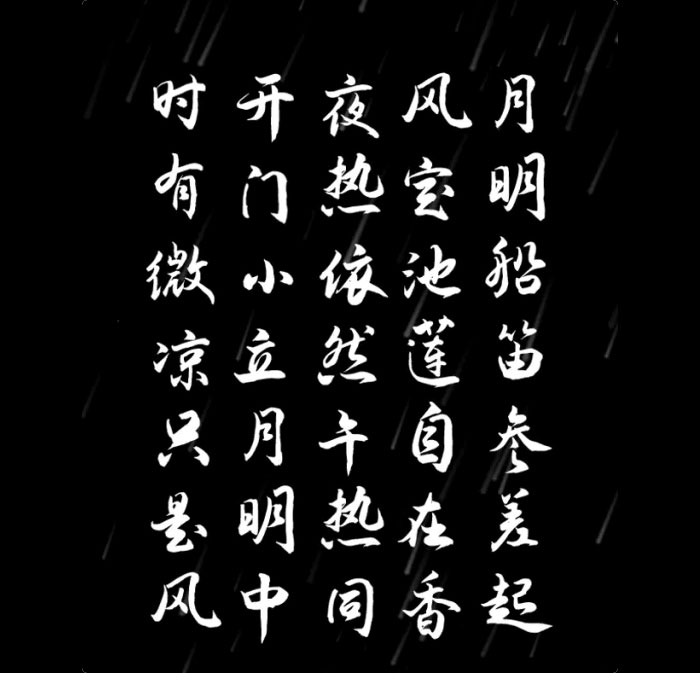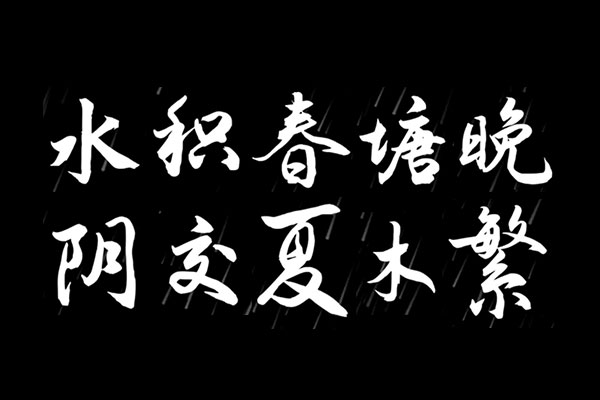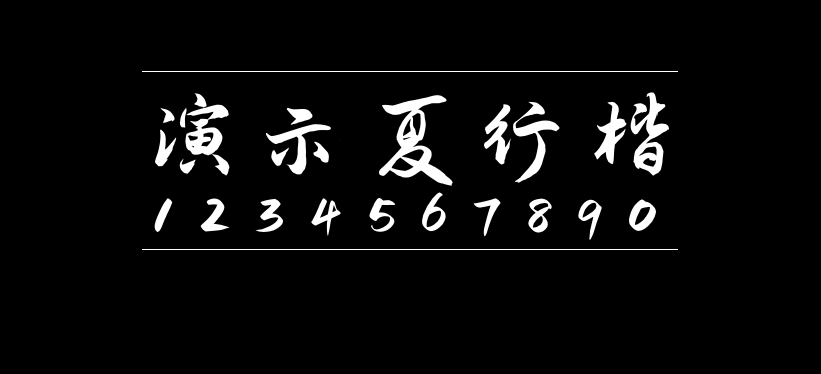
演示夏行楷
演示夏行楷是Keynote研究所的人生哥制作发布的一款毛笔字体。字稿作者是刘锡栋:中国漓江书画艺术家协会理事丨北京中国书画研究院研究员丨中国民族硬笔书法家协会会员丨中国楹联学会会员丨黑龙江楹联家协会会员丨高级政工师,已退休
该字体简体中文行楷,包含标准的6763个字符。
以下为作者原文的引用:
你好,这里是 Keynote研究所,我是人生哥。
设计,重要的是,如何解决用户所面临的当前问题
两年前,为了解决在 Keynote 中文字不能倾斜的问题,我做了一次大胆的尝试:自己动手改造出一款 Keynote 可用的倾斜字,让幻灯片设计师可以在Keynote中一键倾斜文字。于是基于对谷歌开源字体「思源黑体」的倾斜处理,便有了 — 演示斜黑体。但很多人说,这款字应该叫做 演示斜杠体,因为是它,让关于我的故事不再是只有PPT,又加上了一道斜杠——字体。
优秀幻灯片,集巧妙的逻辑编排与可视化图形语言于一身,使原本枯燥的内容,变得更加易懂且利于表述,甚至可以引起大范围传播
发展到今天,PPT 已经不局限于“大字报工具”,它更像是一个多媒体容器,集合了图形语言、图标元素、风格字体、图片视频、3D模型·········从“实用为先”到兼顾“策略与颜值”的双重美学。甚至,它已为很多人创造了就业机会,当然也包括我。
商业幻灯片委托,不仅要帮客户完成项目,更要帮他们规避风险
事实上,大多数风险行为与字体和图片侵权有关,这源自仍有很多企业对于版权意识的淡薄,以及少有能力去支付高昂的授权费。虽然字体和图片被称作是设计师的“油盐酱醋”,但实际情况却是:好字体不敢用,好图片没钱用。所以,我希望为它做一些更有价值的事情。于是便有了《演示新手书》与《演示镇魂行楷》两款字体,皆为幻灯片而生的实用字体!当然,也要特别感谢 P 圈的众多朋友,让这两款现在看来依旧很不成熟的字,出现在了越来越多的重要的演示场合,让它们源于演示,也不止于演示。
这两年,关于字体的世界,在悄然发生着变化
越来越多的免费商用字体、平价字体,如雨后春笋般一个接一个地发布出来。有标准字,有手写字,有美术字 ······
如:阿里巴巴、OPPO、字魂网、站酷网、途牛UED、喜鹊造字、字由、方正字库、汉仪字库、字体传奇、素材市集&Elephant、锐字家族、优设网、刘鹏、刘兵克、胡晓波、庞门正道阿门、wixette、心光工作室、落霞孤鹜、黄令东、字体树黄煜臣、杨任东、鸿雷、字体圈DESIGN、造字工房、卓米品牌设计、卢帅、春颜秋色、谦度、Siue、林芳柽、李雨、叶根友、黄引齐 ······
要感谢上述这些企业和个人让每个中国设计师,有字可用,有好字可用。
演示新手书与演示镇魂行楷,这两款字体于我而言,意义重大,但谩骂声也从未停止
熟话说:武无高低,唯用武之人有强弱之别。茶无贵贱,唯品茶之人一杯以入心。我左右不了任何人,我的态度是:如果你觉得好看,就用。一款字体无人可用将会是它最大的悲哀,能把字体用起来就是对作者最大的帮助。如果你觉得不好看,就别用,我并不欠任何人。
今年3月,我发布了两款免费可商用手写字体
演示佛系体 和 演示悠然小楷 分别来自纪国才老先生和孟祥媛同学的手写字稿。得益于在做字技术上的突破,从字稿到字体的封包效率几乎越来越快,已经可以实现3天内结束字体封包。今天我将再次发布三款免费可商用字体,全部为半自动流程制作,当然我也已经做好了被某些人骂的准备,似乎一切手写字体都天生具备这种基因,所以,请让你们的狂风暴雨来的更猛烈一些吧!这三款字分别为:演示春风楷、演示夏行楷、演示秋鸿楷。